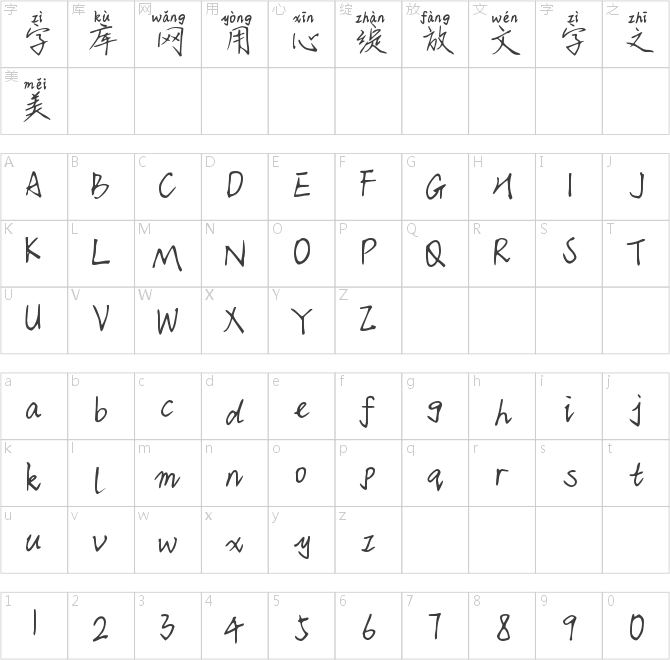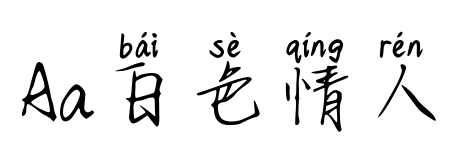
字體名稱: Aa白色情人
Aa白色情人
Aa白色情人介紹
Aa白色情人字體白色情人字庫(kù)是一款讓人賞心悅目、百看不厭的中文字體,適合各類廣告和產(chǎn)品包裝設(shè)計(jì)應(yīng)用,字體大小7.5MB,格式為ttf字體,上傳用戶是Aa字庫(kù),作者/版權(quán)方為Aa字庫(kù)